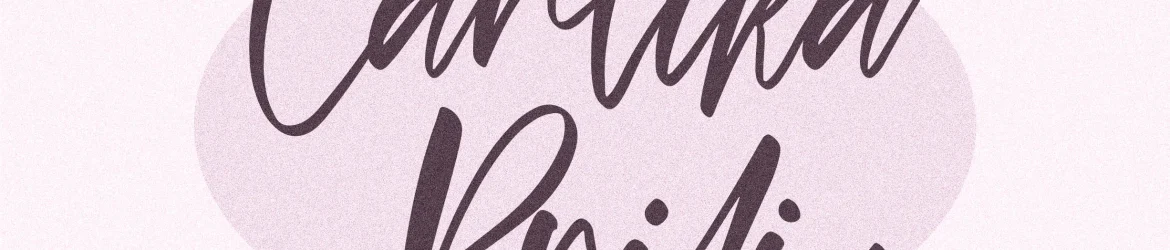
A fonte “Cantika Prilia” é uma opção perfeita para quem busca personalidade e charme em projetos digitais. Se você está procurando por uma mão escrita que dê vida a sua criação, esta fonte é a escolha ideal. Ela foi projetada para uma variedade de aplicações, desde logotipos e materiais de embalagem até convites e cartões de presente. A “Cantika Prilia” se destaca em ambientes que valorizam um toque humano, onde cada detalhe importa. Seja você designer gráfico, ilustrador ou editor de fotos, esta fonte oferece a oportunidade de incorporar elementos únicos e autênticos às suas criações. Seja ela o texto no seu próximo design de logotipo, ou uma citação sobre o produto em sua embalagem customizada, “Cantika Prilia” traz personalidade e elegância para qualquer projeto. Sua capacidade única de adaptar-se a diversos estilos e tipos de projetos torna-a um recurso indispensável para designers que desejam adicionar uma cara mais pessoal ao seu trabalho. Com sua mão escrita cuidadosamente elaborada por perspectype, “Cantika Prilia” é o elemento chave para dar vida aos seus designs. Não se esqueça de experimentar sua versatilidade – do design de publicações até a criação de fotografias e até mesmo em projetos que exigem um toque especial, como etiquetas ou marcas. A “Cantika Prilia” traz à tona o seu mais profundo desejo de criar algo único e memorável.